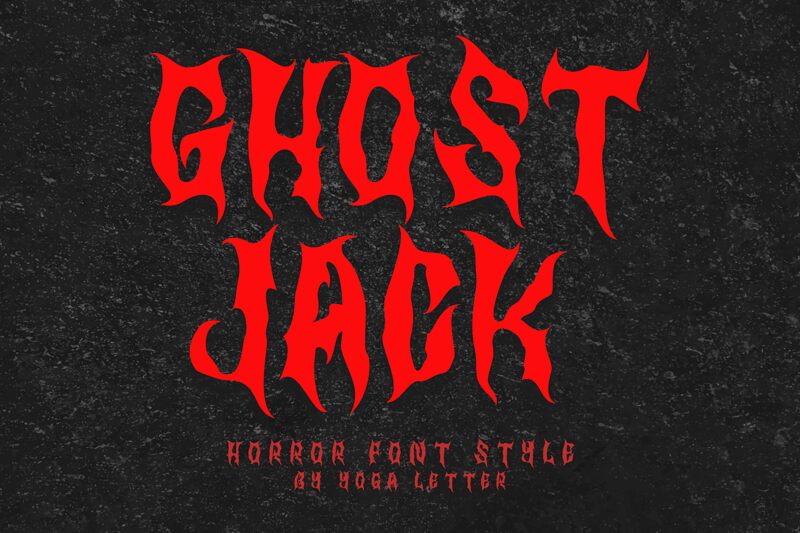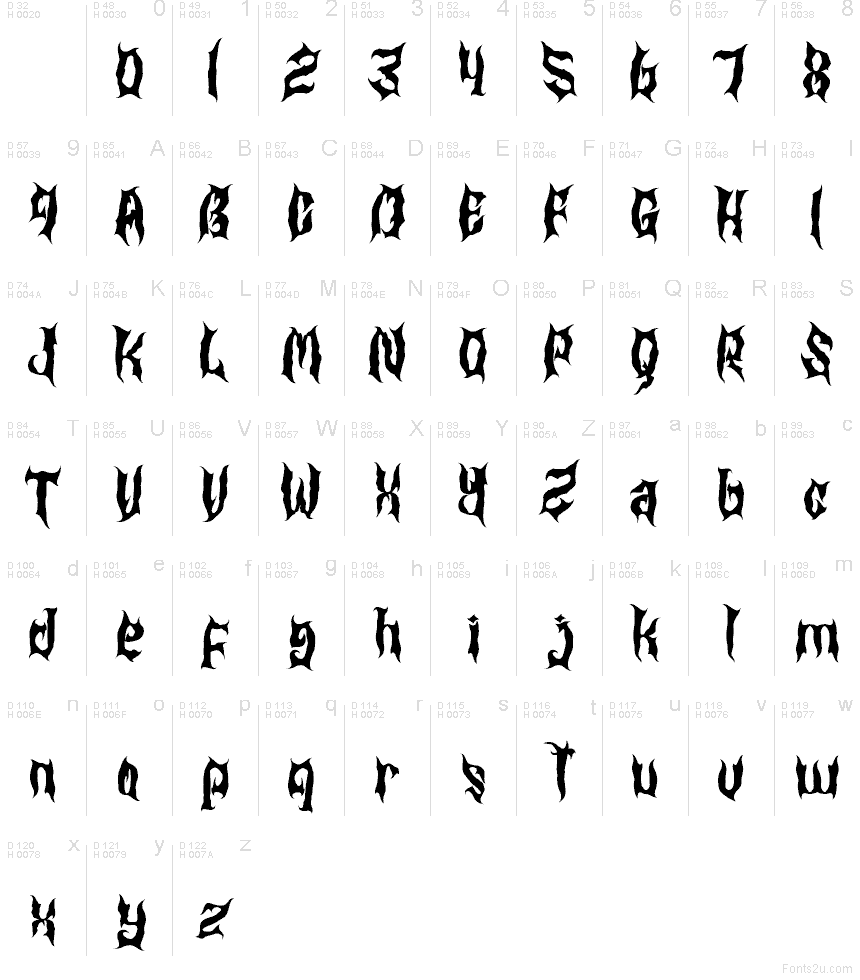
Ghost Jack Demo
Ghost Jack, de Yoga Letter, es una tipografía gratuita para Halloween que destaca por sus trazos dentados similares a llamas y sus extremos afilados en forma de gancho. Sus letras presentan un aspecto irregular y retorcido, con remates puntiagudos que le dan a todo el conjunto una estética espectral, como si estuviera cortada a mano.
Ghost Jack es una fuente gratuita ideal para pósteres de Halloween, invitaciones a fiestas de miedo, carteles de casas encantadas, folletos de truco o trato y gráficos para juegos de terror. Sus formas sinuosas también funcionan muy bien en logotipos temáticos, tarjetas de título y textos decorativos que necesiten un toque oscuro y estacional.